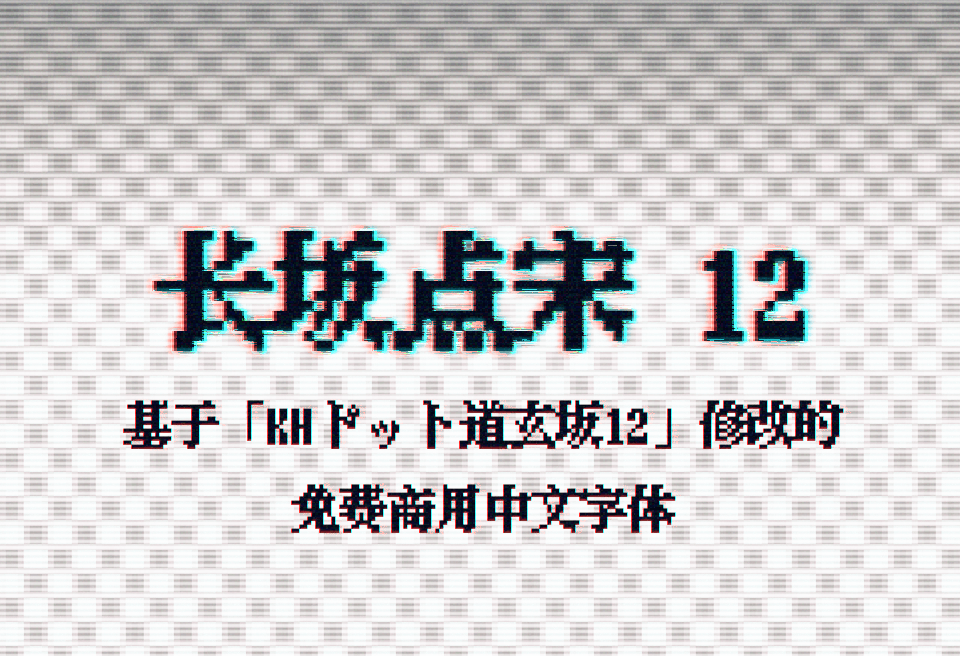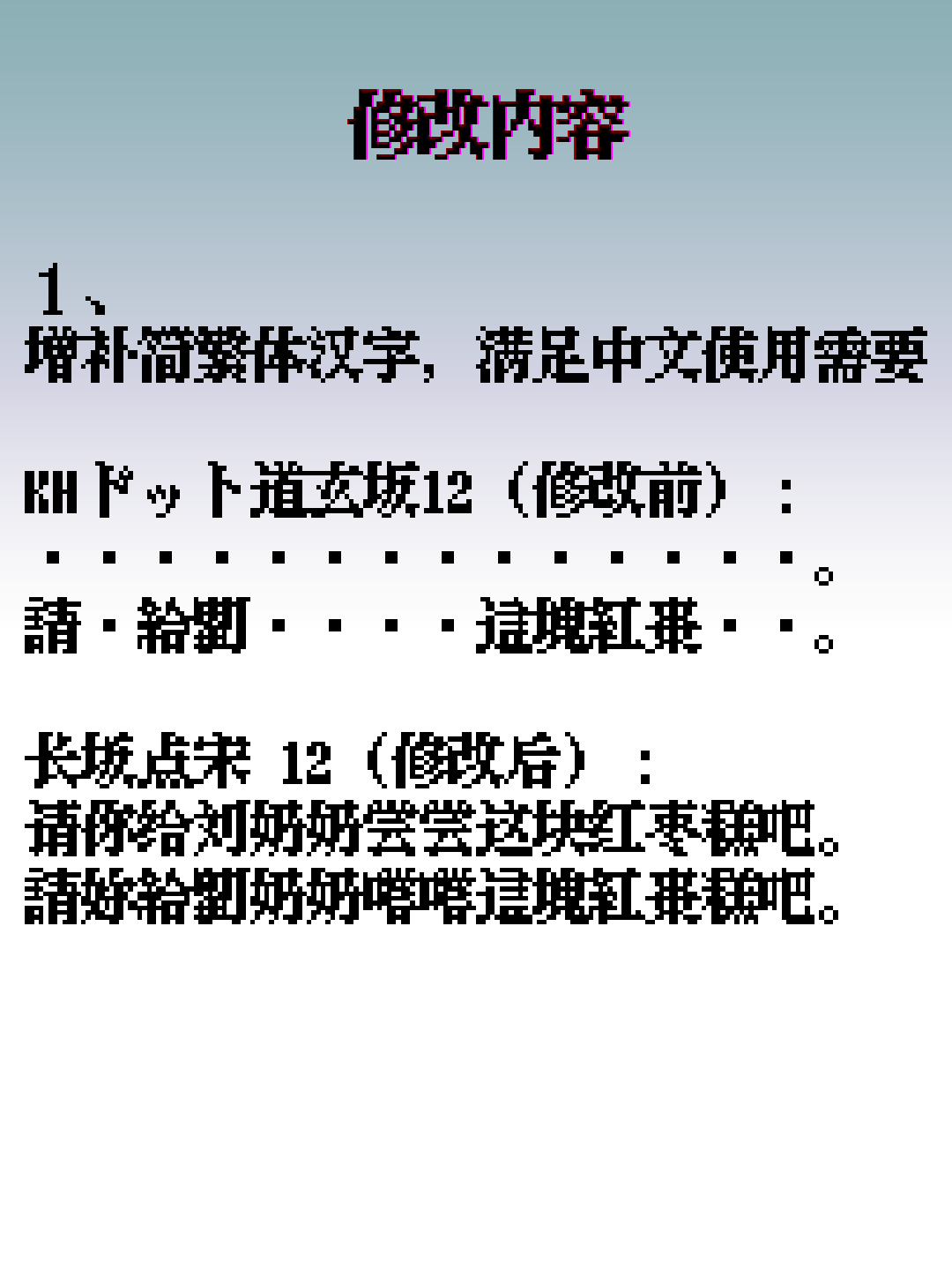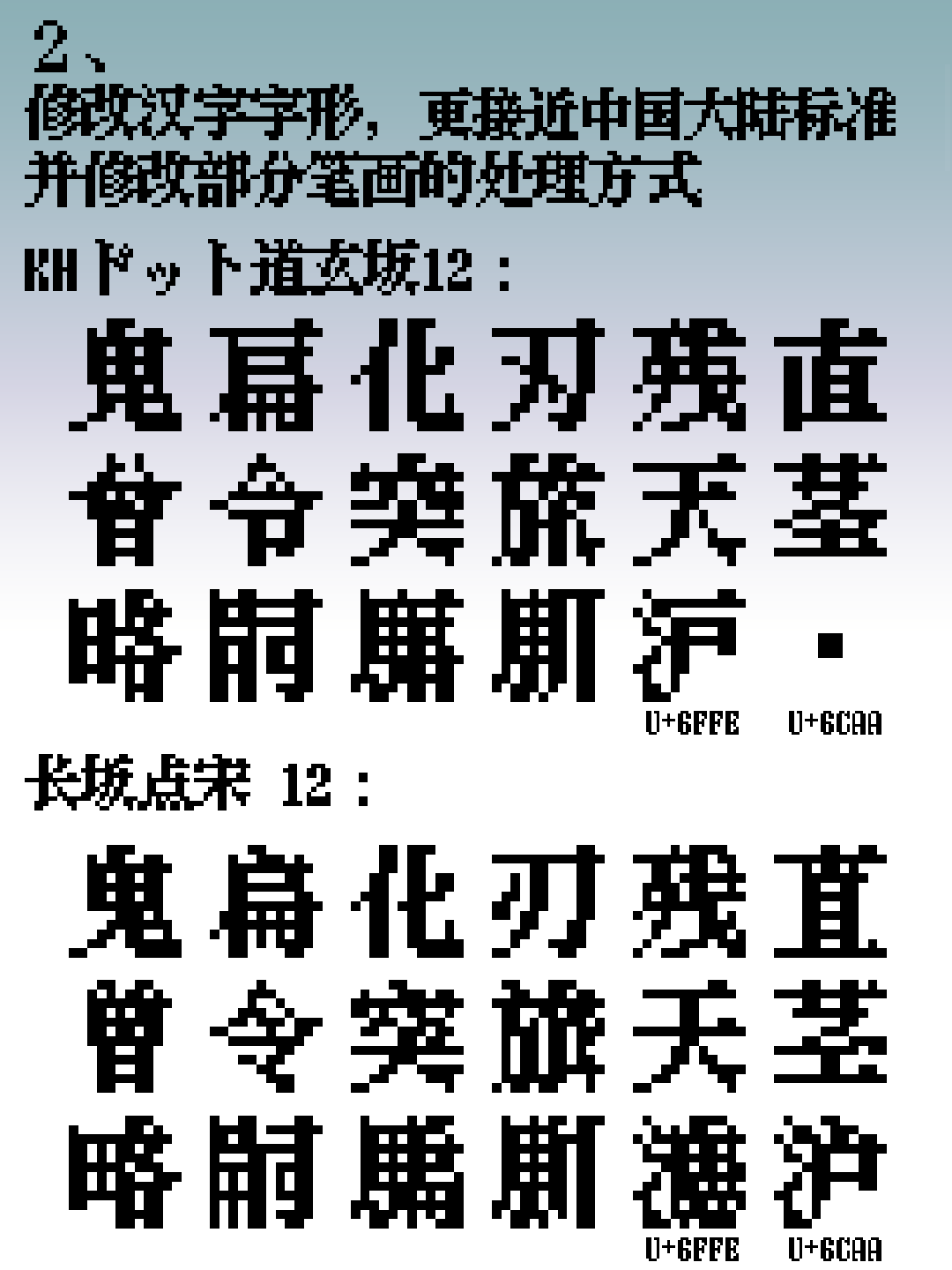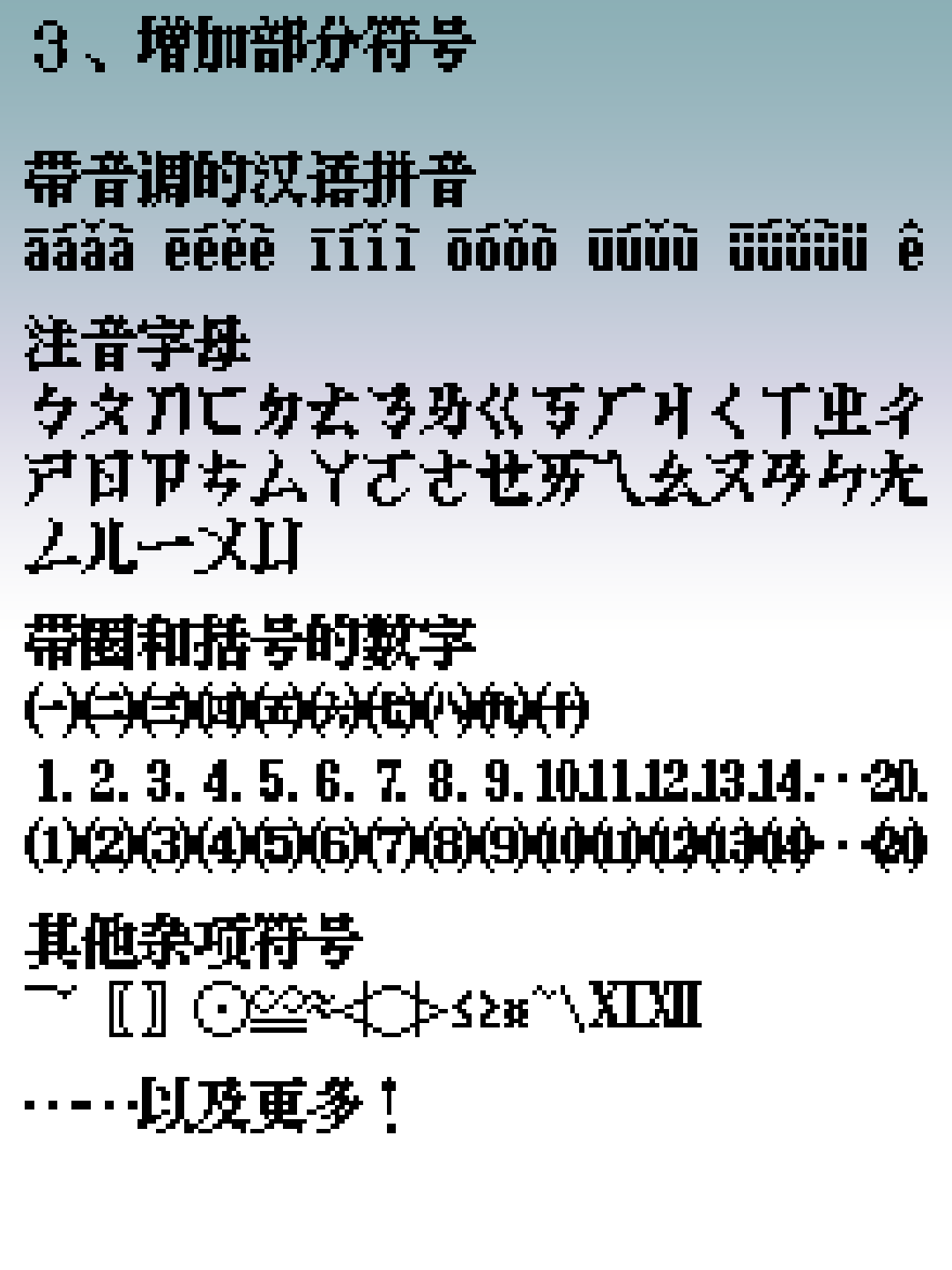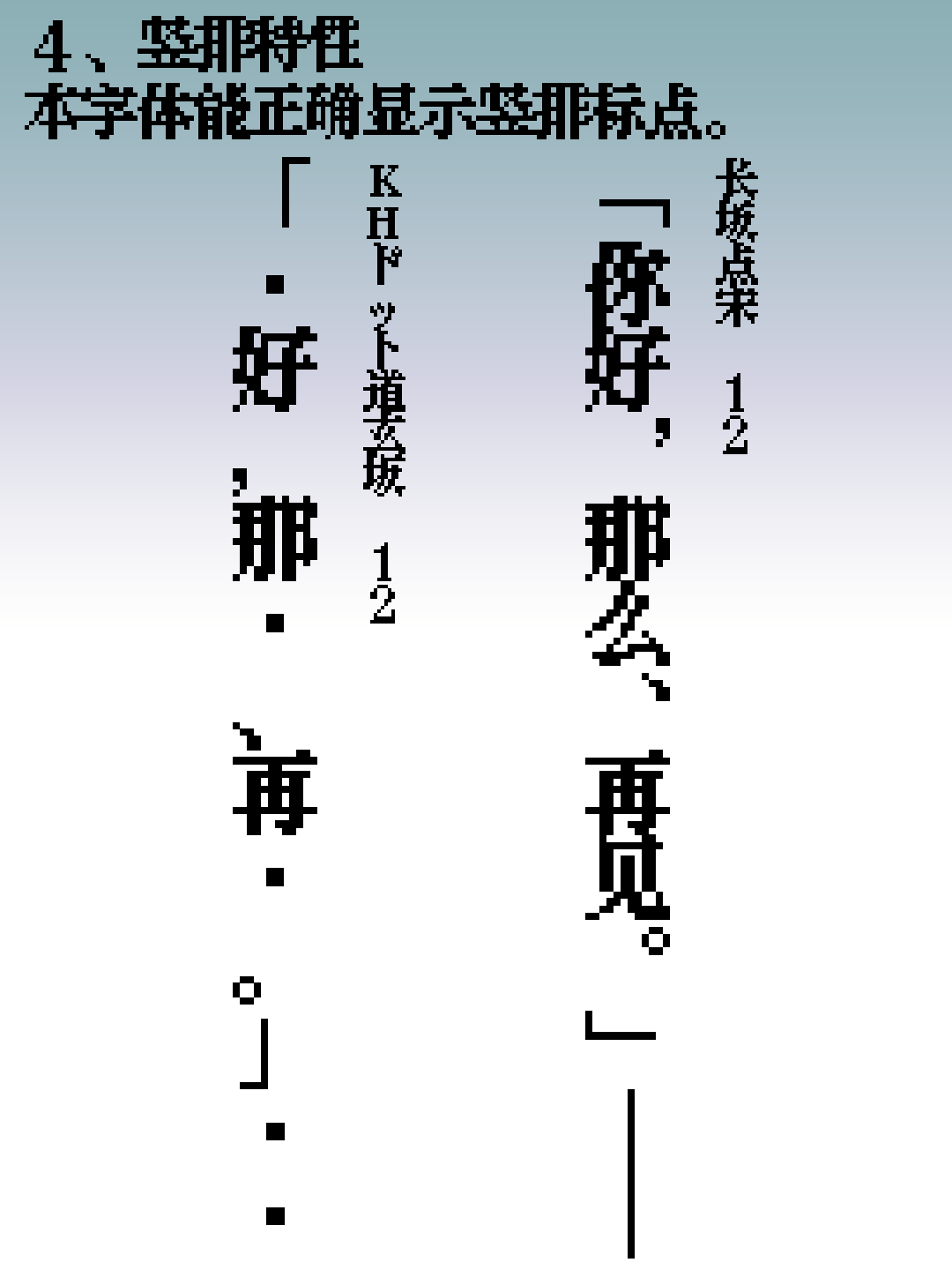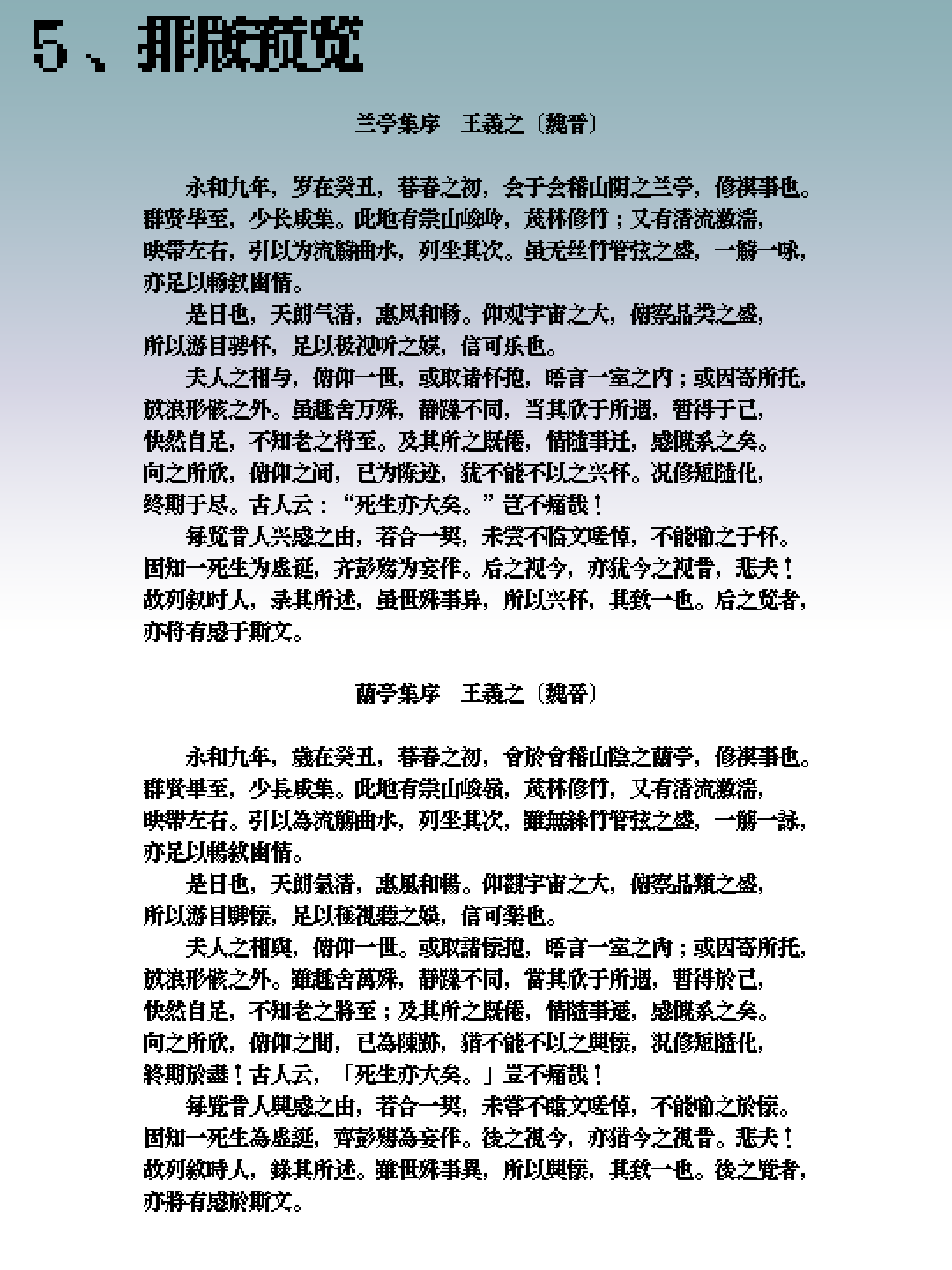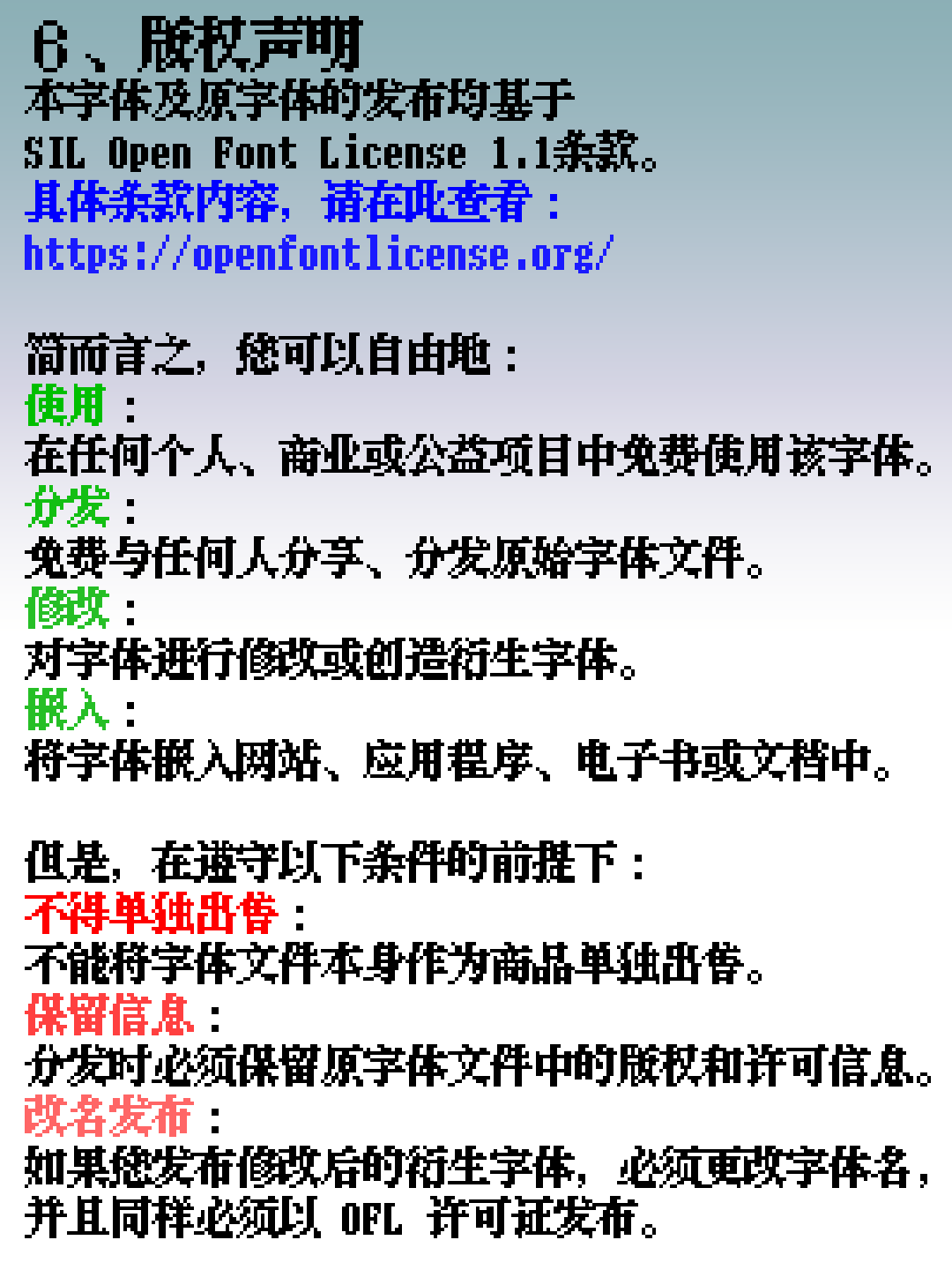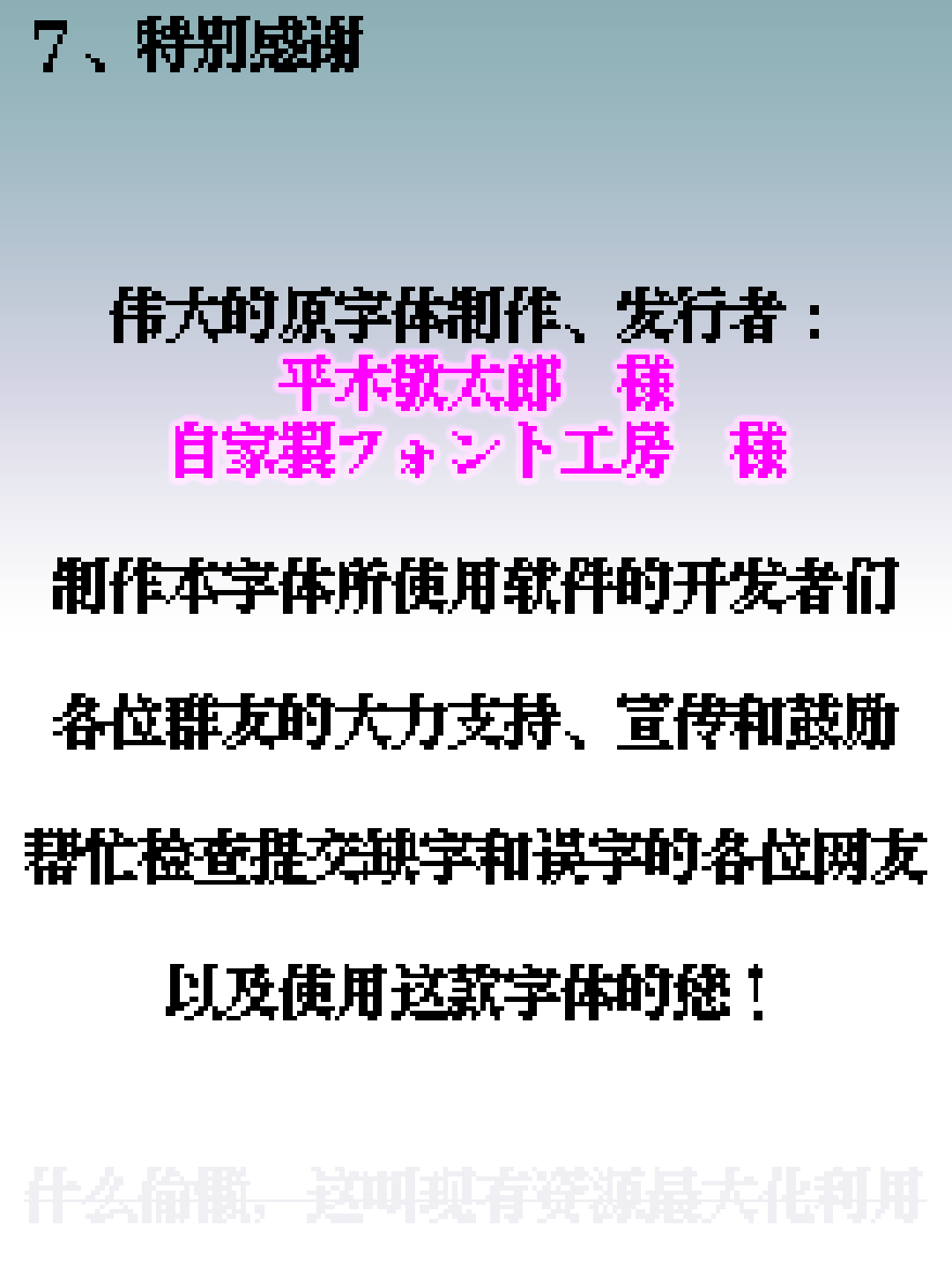
「长坂点宋 12」是一款经过精心设计与打磨的12像素点阵字体,其创作根源可追溯至经典的「KHドットフォントシリーズ」字体系列中的「KHドット道玄坂12」。该字体不仅继承了原版的精髓与点阵韵味,还在其基础上进行了全面的优化与扩展,特别补全了现代简体中文的完整字符集,并兼顾收录了部分高频使用的繁体中文字符,从而显著拓宽了其在各类数字媒体与设计项目中的适用性与实用性。 从视觉风格上而言,「长坂点宋 12」可以被视为传统粗宋体在像素化时代的生动再现。其笔画结构在极有限的像素网格中依然力求清晰、有力、分明,每一笔都体现出果断与扎实的质感,呈现出浓郁的复古数字美感。这种独特的点阵构成方式,与宋体本身端庄、略带粗犷的字形特征相结合,碰撞出一种既经典又充满年代感的视觉语言。 正因如此,「长坂点宋 12」尤其适合应用于那些追求怀旧与复古氛围的设计场景中。例如,它可以完美融入复古风格游戏的用户界面、菜单文字、对话框文本,或是各类街机、老式计算机主题的标题与提示信息。此外,在网页设计、独立游戏、像素艺术作品以及具有年代感或街机风格的招牌、标识与海报设计中,使用该字体也能为整体作品增添独特、地道且富有故事性的视觉韵味,瞬间唤起观众对于早期数字时代的共同记忆。